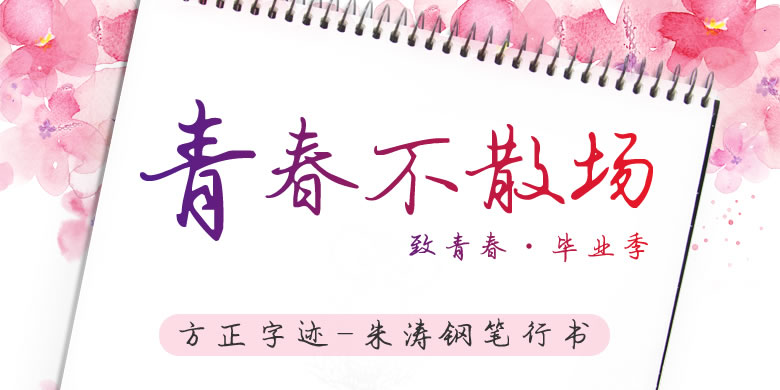
字体介绍 品牌:方正字迹设计师:朱涛发行时间:2013字库编码:大陆简体(GB2312-80)、大陆繁体(GB12345-90)分类:常规书写·硬笔 英文名称:.TTF 方正字迹-朱涛钢笔行书由书法家朱涛先生创作。这款字体书写规范,结构端正,是一款堪做硬笔范本的钢笔字体。 其风格平正中和, 适用于现代诗歌、短文的排版,以及文化、商业类品牌的广告语设计。 字体下载 官方下载